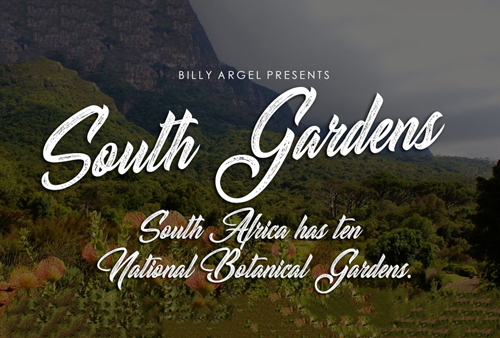
South Gardens Font – Download Grátis
A South Gardens Font é uma deliciosa escolha para quem está procurando por uma fonte script com uma aparência natural e encantadora. Criada pelo designer Billy Argel, essa fonte tem um charme próprio que se destaca nas criações digitais, especialmente em projetos pessoais ou iniciantes no design gráfico. Ideal tanto para pequenos detalhes quanto para letras maiores, a South Gardens é uma solução versátil de fontes script. Ela captura o espírito delicado e elegante do estilo script sem parecer artificial. O resultado é um texto que toma forma, ganhando vida em cada palavra escrita. Com um design natural e elegante, a South Gardens é perfeita para aplicações de design gráfico onde um touch de personalidade seja bem vindo. Suas linhas fluidas e curvas suaves enriquecem qualquer texto que ela embute, tornando-a uma fonte indispensável para quem quer dar um toque único em suas criações. A South Gardens é a escolha ideal para os designers gráficos aficionados ou iniciantes, pois possui um design simples e reconhecível. Como com todas as fontes da Billy Argel, é parte de uma ampla gama de fontes script que oferece uma variedade incrível para quem deseja explorar diferentes estilos. Completos em versões comerciais disponíveis através do site oficial de Billy Argel (billyargel.com), a South Gardens pode ser usada com facilidade em diversos projetos pessoais e profissionais, sejam eles grandes ou pequenos. Para mais informações e para obter licenças completas ou comerciais da fonte, você pode entrar em contato diretamente por email (). Acesse também o site principal de Billy Argel (www.billyargel.com) ou sua página oficial no Facebook (www.facebook.com/billyargelfonts).